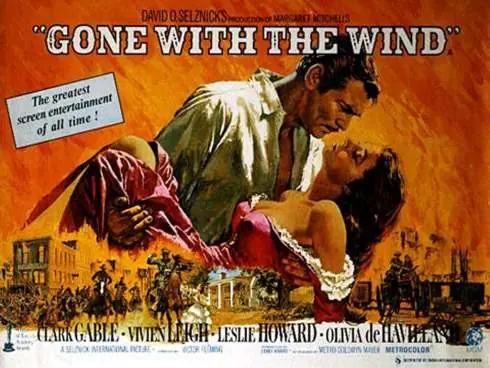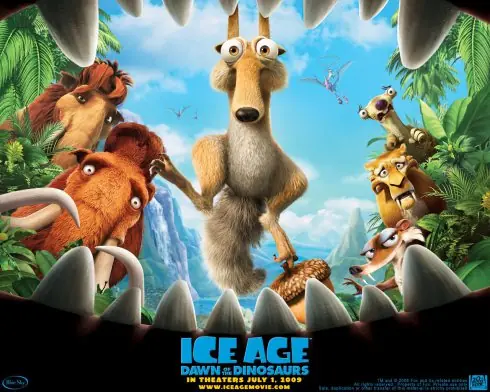
1. 28 Días Después
Película dirigida por Danny Boyle y protagonizada (entre otros) por Cillian Murphy. La tipografía ha sido diseñada por Jens R. Ziehn. Puedes descargar la fuente de forma gratuita haciendo click
2. 300
Esta película dirigida por Zack Snyder es la adaptación cinematográfica de la serie de cómics del mismo nombre de Frank Miller, la cual relata la Batalla de las Termópilas. No hemos encontrado la fuente original de esta tipografía, pero una que se asemeja bastante es la Adam Warren, diseñada por Press Gang Studios y que puedes descargar gratis para uso personal haciendo click
3. 2001: Una odisea en el espacio
Esta película de Ciencia Ficción dirigida por Stanley Kubrick (en 1968), marcó un hito por su estilo de comunicación visual, sus revolucionarios efectos especiales, su realismo científico y sus proyecciones vanguardistas. La tipografía usada en esta película es Futura, de la cual ya hemos hablado en este blog (ver entrada “
“). La afinidad del Kubrick por las tipografías sans serif queda patente en sus obras, entre las que también se encuentra Eyes Wide Shut (donde también usó Futura)
4. Alicia en el país de las maravillas
En esta versión de la novela de Lewis Carroll dirigida por Tim Burton, la tipografía elegida se trata de Alice in Wonderland. La fuente original no la hemos localizado, así que os dejamos la que ha diseñada Marco Trujillo López basada en los caracteres del título de la película. Puedes descargarla de forma gratuita para uso personal haciendo click
5. Amelie
Film dirigido por el francés Jean-Pierre Jeunet que relata la vida de la camarera Amélie (Audrey Tautou) que decide cambiar su vida el mismo día que Lady Di fallece en un accidente de tráfico. En este caso, la tipografía utilizada es laChampion™ BQ, diseñada por Günter Gerhard Lange para la compañía Berthold in 1957. Es una tipografía de pago que puedes adquirir en la propia página de Berthold (
6. Apocalypse Now
Película bélica dirigida por Francis Ford Coppola (en 1979) basada en la novela de Joseph Conraden “El corazón de las tinieblas” (Heart of Darkness). En esta película, la tipografía fue diseñada por Jens R. Ziehn y puedes descargarla de forma gratuita haciendo click
7. Austin Powers
En esta comedia escrita y producida por el actor Mike Myers y dirigida por Jay Roach (quien dirigió las dos posteriores secuelas.
), eligieron una desenfadada tipografía denominada Action Is, diseñada por B.O. Nelson y que puedes descargar de forma gratuita haciendo click
8. Avatar
Superproducción de ciencia ficción, escrita, producida y dirigida por James Cameron (en 2009). La tipografía elegida seguramente la conocerás por ser bastante habitual. Es la Papyrus Regular, diseñada por Chris Costello para Linotype. Es una fuente de pago que puedes descargar desde su propia web (
9. Volver al Futuro
Esta película es todo un icono cultural y una de nuestras favoritas. Escrita y dirigida por Robert Zemeckis, producida por Steven Spielberg y protagonizada por Michael J. Fox y Christopher Lloyd. Su característica tipografía, diseñada por Cyril Bourreau, puedes descargarla de forma gratuita haciendo click
10. Batman Forever
Producida por Tim Burton y dirigida por Joel Schumacher, esta película está basada en el personaje de DC Comics, Batman. Puedes descargar la tipografía de forma gratuita desde
11. Blade Runner
Película de ciencia ficción, dirigida por Ridley Scott, basada en la novela de Philip K. Dick “¿Sueñan los androides con ovejas eléctricas?”. Esta tipografía futurista, diseñada por Phil Steinschneider, la puedes descargar gratis haciendo click
12. Casablanca
Clásico entre los clásicos. Película dirigida en 1942 por Michael Curtiz, narra un drama romántico en la ciudad marroquí de Casablanca entre los protagonistas Humphrey Bogart -en el papel de Rick Blaine- e Ingrid Bergman -como Ilsa Lund-. Basada en la obra teatral “Everybody comes to Rick’s” de Murray Burnett y Joan Alison. Aunque no hemos encontrado la tipografía original porque realmente no es una tipografía sino que consiste en “Lettering”, hemos hecho algunas pruebas y encontrado dos fuentes similares: La Curly Joe -diseñada por JOEBOB graphics- y la Brush Script -diseñada por Peax Webdesign-, que puedes descargar haciendo click
13. Celebrity
Las letras de este film dirigido por Woody Allen en 1998 refleja la pasión que el directo neoyorquino siente por la tipografía EF Windsor™ Elongated y EF Windsor Light Condensed (que puedes observar en infinidad de sus películas). Ambas tipografías son de pago y puedes adquirirlas en distintos sitios (
14. La novia cadaver
Película dirigida por Tim Burton y Mike Johnson utilizando la técnica stop motion. La tipografía usada en el título es laBeynkales, de pago, que puedes adquirir en varios sitios (
30. La Lista de Schindler
Película dirigida por Steven Spielberg que cuenta la historia de Oskar Schindler, un empresario alemán que salvó la vida de alrededor de 1100 judíos polacos durante el Holocausto. La tipografía original elegida en este caso no la hemos localizado, así que os dejamos la la Schindler’s Font diseñada por Juan Casco basándose en los caracteres tipográficos del título de la película y que puedes descargar para uso personal haciendo click